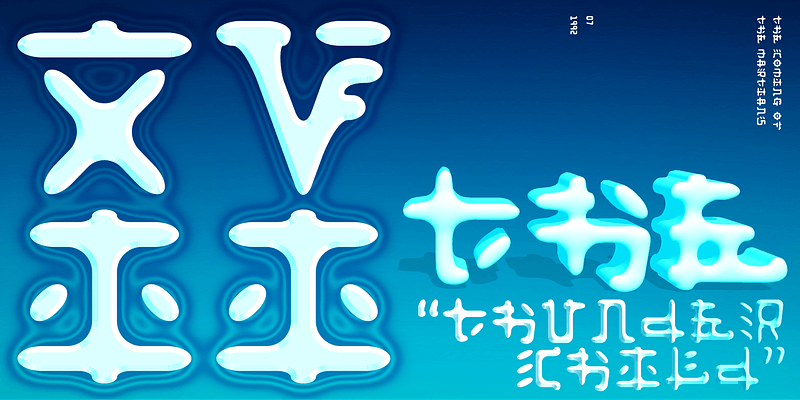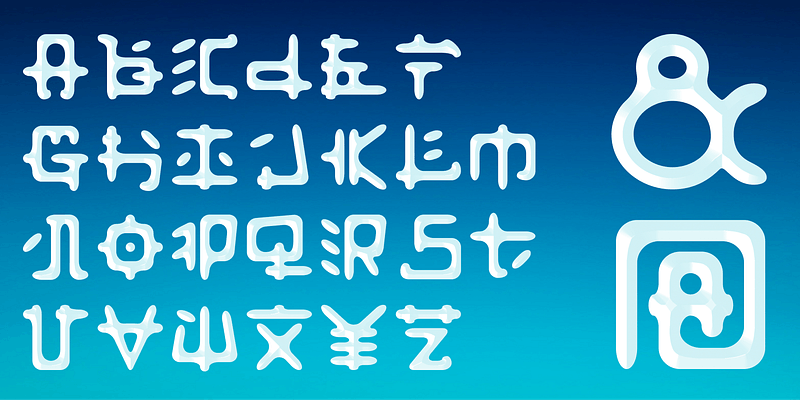
Fusaka è stato creato dal grafico e co-fondatore della foundry di caratteri P22, Michael Want. Fusaka è un carattere tipografico di visualizzazione altamente originale e specializzato che collega gli stili Kanji e la forma delle lettere romane. Come nei Kanji, ogni carattere si inserisce in un quadrato. Ciò accentua l’aspetto a prima vista di Fusaka, come il cinese o il giapponese, e consente di impostarlo orizzontalmente o verticalmente. Usa Fusaka per un effetto unico e sorprendente su copertine di CD, titoli di riviste, titoli di libri e siti Web. U.S. Patent Design 405.106.